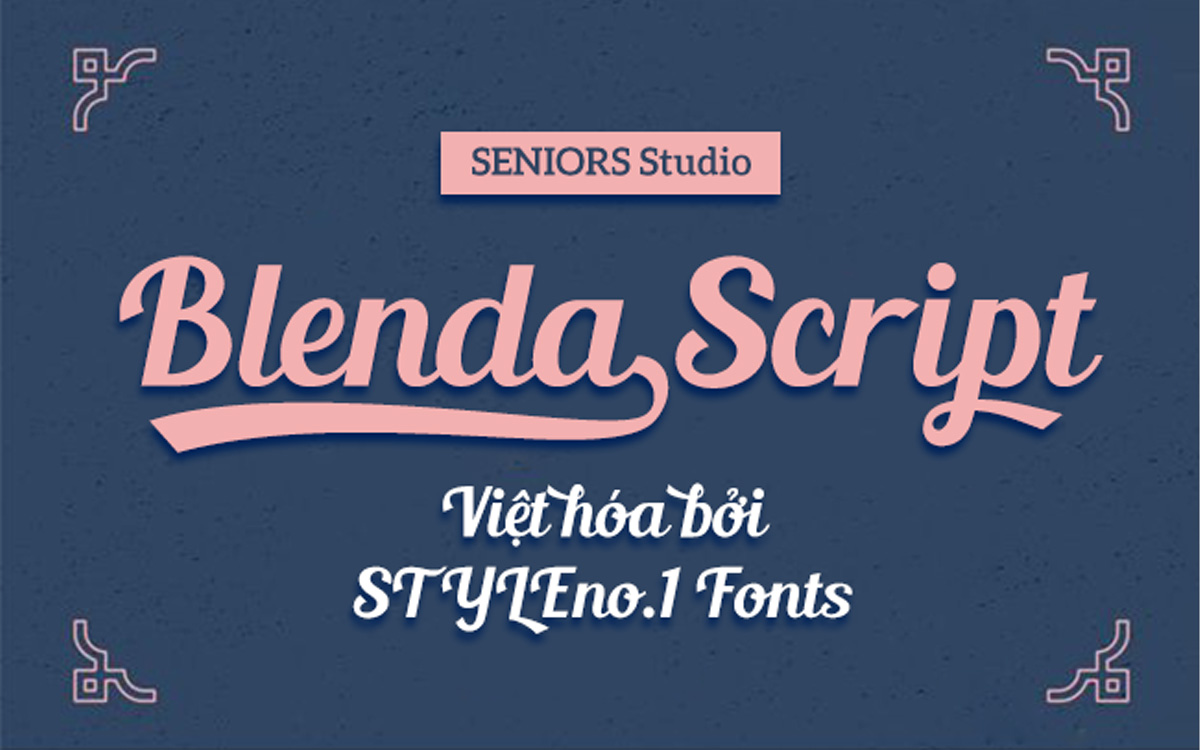
Font chữ nghiêng mềm mại sang trọng SVN-Blenda Script
Trong thế giới thiết kế đồ họa hiện đại, việc lựa chọn phông chữ phù hợp đóng vai trò quyết định đến cảm xúc và thông điệp mà thương hiệu muốn gửi gắm. Nếu bạn đang tìm kiếm một phông chữ vừa mang nét cổ điển quyến rũ, vừa toát lên vẻ thanh lịch và hiện đại thì SVN-Blenda Script chính là giải pháp hoàn hảo. Với các đường nét uốn lượn tinh tế, bộ font chữ nghiêng mềm mại sang trọng này sẽ biến mọi ấn phẩm thiết kế của bạn thành một tác phẩm nghệ thuật đầy sức hút.
Trải Nghệ Thuật Typography Đỉnh Cao Với Font Chữ Nghiêng Mềm Mại Sang Trọng SVN-Blenda Script Việt Hóa
SVN-Blenda Script là phiên bản Việt hóa trọn vẹn từ bộ font gốc Blenda Script – một phông chữ vintage script độc đáo được lấy cảm hứng từ phong cách typography cổ điển của thập niên trước nhưng được cải tiến để phù hợp với thị hiếu thẩm mỹ đương đại. Nhờ vào sự kết hợp giữa nét thanh nét đậm uyển chuyển và góc nghiêng chuẩn xác, bộ font này mang lại cảm giác cực kỳ cao cấp, lãng mạn và quý phái.
Được thực hiện bởi đội ngũ SVN (Subtle Việt Nam), phiên bản Việt hóa đã tối ưu hóa toàn bộ hệ thống dấu thanh tiếng Việt, đảm bảo tính cân đối và thẩm mỹ khắt khe nhất. Đây là sự lựa chọn ưu tiên hàng đầu dành cho các nhà thiết kế đồ họa, thương hiệu thời trang, tiệm trang điểm, studio cưới và những ai yêu thích phong cách thiết kế tinh tế.
1. Đường Nét Mềm Mại, Uyển Chuyển Và Đầy Tinh Tế
Điểm nổi bật đầu tiên giúp SVN-Blenda Script chinh phục giới thiết kế chính là cấu trúc nét chữ vô cùng mượt mà. Sự biến chuyển nhịp nhàng giữa các nét thanh mảnh kéo dài và các nét đậm chắc chắn tạo nên một nhịp điệu thị giác bay bổng, thu hút người xem ngay từ cái nhìn đầu tiên.
Góc nghiêng tự nhiên của phông chữ được tính toán tỉ mỉ, gợi liên tưởng đến những dòng chữ viết tay thủ công của các nghệ nhân calligraphy tài hoa. Sự mềm mại này giúp sản phẩm xóa bỏ vẻ khô cứng của các font chữ thông thường, thay vào đó là một thần thái sang trọng, quyến rũ và ấn tượng.
2. Hỗ Trợ Tiếng Việt Chuẩn Thẩm Mỹ Với Bộ Dấu Hoàn Hảo
Thách thức lớn nhất khi dùng các bộ font script từ nước ngoài là các dấu thanh tiếng Việt (sắc, huyền, hỏi, ngã, nặng, các dấu ê, ô, ơ, ư…) thường bị lỗi vị trí, đè nét hoặc phá vỡ cấu trúc uyển chuyển của chữ. Với SVN-Blenda Script, vấn đề này đã được xử lý triệt để.
Bộ dấu tiếng Việt trong font được thiết kế tỉ mỉ, đồng điệu với nét uốn nghiêng của chữ gốc. Các dấu thanh được đặt ở vị trí vô cùng tự nhiên, giúp văn bản tiếng Việt hiển thị mượt mà, chuẩn nét mà không bị rối mắt hay mất đi sự thanh lịch vốn có.
3. Tích Hợp Bộ Ký Tự Thay Thế (OpenType Features) Phong Phú
SVN-Blenda Script mang đến không gian sáng tạo vô tận nhờ tích hợp hệ thống OpenType nâng cao. Người dùng có thể dễ dàng truy cập vào hàng loạt ký tự thay thế (Alternate Glyphs), các đường gạch chân nghệ thuật (Swashes) và bộ ký tự nối (Ligatures) đa dạng.
Nhờ những tính năng này, bạn có thể tự do biến tấu các chữ cái đầu từ hoặc cuối từ thành những đường nét bay bổng độc đáo. Điều này giúp các dòng tiêu đề hay tên thương hiệu trở nên cá nhân hóa hơn bao giờ hết mà không đòi hỏi phải vẽ tay phức tạp.
4. Tính Ứng Dụng Đa Dạng Trong Thiết Kế Thương Hiệu Và Truyền Thông
Sở hữu vẻ đẹp giao thoa giữa cổ điển và hiện đại, font chữ nghiêng mềm mại sang trọng SVN-Blenda Script có tính ứng dụng cực kỳ linh hoạt trên nhiều ấn phẩm truyền thông và bộ nhận diện thương hiệu khác nhau:
• Thiết kế Logo & Brand Identity: Phù hợp hoàn hảo cho các thương hiệu thời trang cao cấp, thẩm mỹ viện, spa, thương hiệu mỹ phẩm, tiệm trang sức hay các quán café phong cách retro/vintage.
• Thiệp mời & In ấn sự kiện: Tạo nên những mẫu thiệp cưới, thiệp mời tiệc VIP lãng mạn, thanh lịch và ghi dấu ấn đậm nét cho người nhận.
• Bao bì sản phẩm: Nâng tầm giá trị cho bao bì nước hoa, hộp quà tặng, nhãn mác chai rượu hay sản phẩm thủ công cao cấp.
• Truyền thông số & Bìa sách: Thích hợp làm điểm nhấn cho tiêu đề tạp chí, banner quảng cáo, poster phim và các hình ảnh truyền thông trên Facebook, Instagram.
5. Khả Năng Hiển Thị Tối Ưu Trơn Tru Trên Mọi Nền Tảng
Bên cạnh yếu tố thẩm mỹ, SVN-Blenda Script được kỹ thuật hóa đạt chuẩn cao. Khoảng cách giữa các chữ cái (kerning) được căn chỉnh chuẩn xác, đảm bảo chữ không bị dính nét hay quá rời rạc dù hiển thị ở kích thước biển hiệu lớn hay màn hình di động nhỏ.
Hướng Dẫn Phối Hợp Font Chữ Giúp Thiết Kế Trở Nổi Bật Hơn
Để khai thác tối đa vẻ đẹp của font chữ nghiêng mềm mại sang trọng SVN-Blenda Script, bạn nên áp dụng một số nguyên tắc phối font chuyên nghiệp dưới đây: